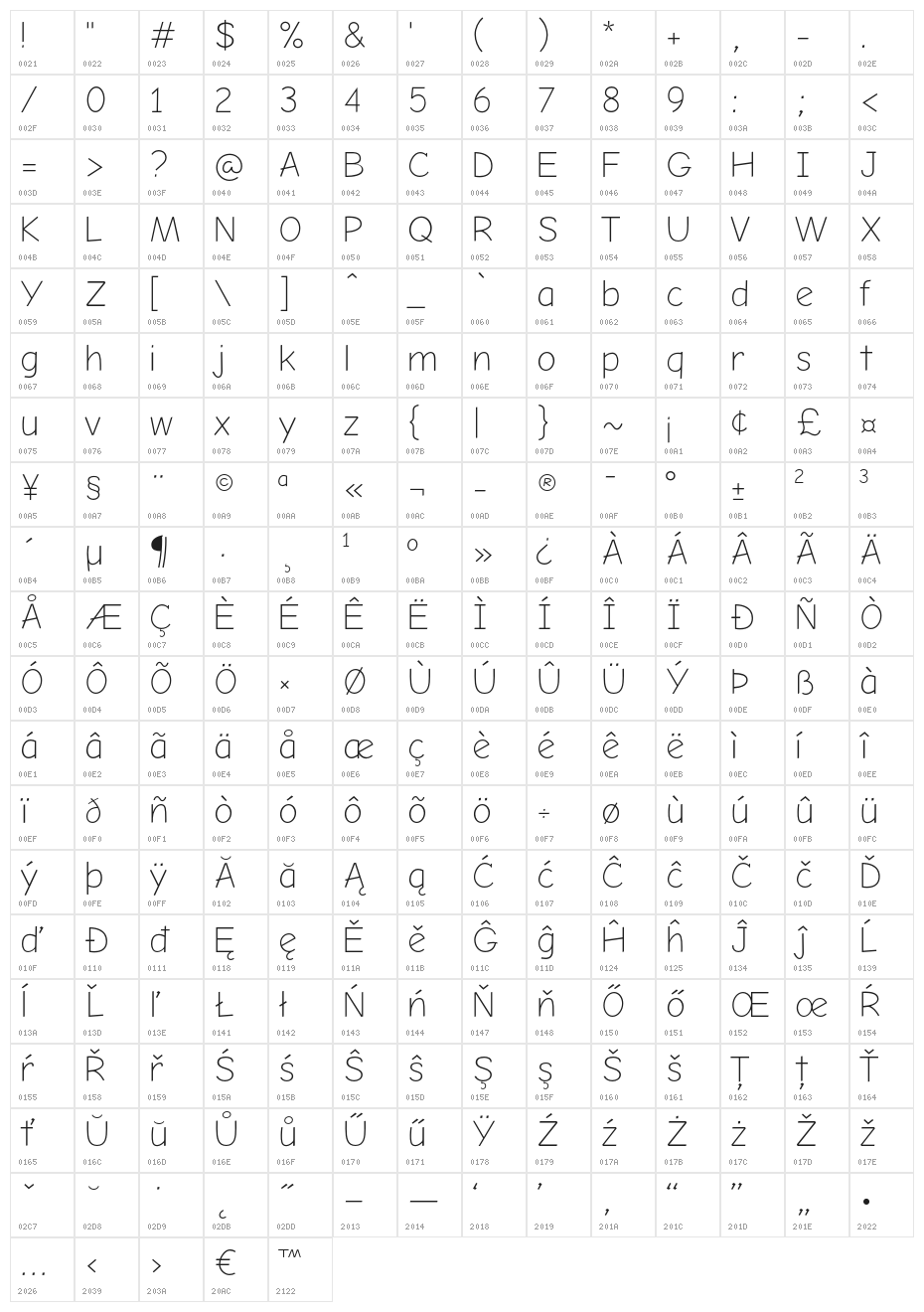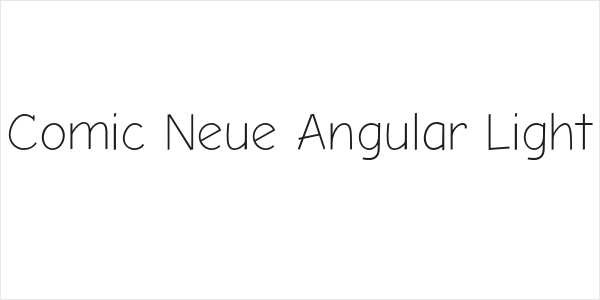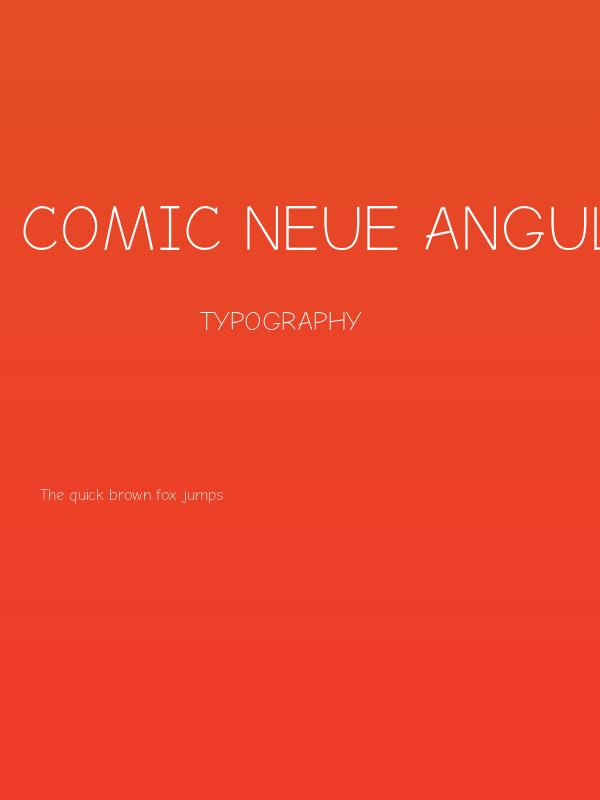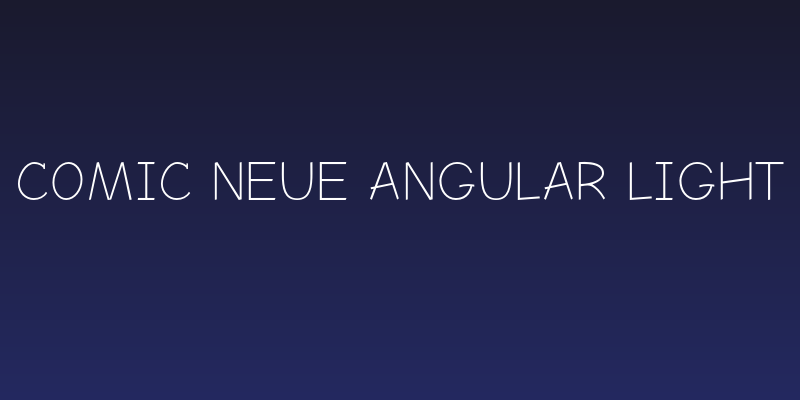
Comic Neue Angular Light Font
| Anwendungsfall | Headlines, Body text, Logos |
| Vorgeschlagene Projekte | Ideal for children's books, casual branding, and modern web design. |